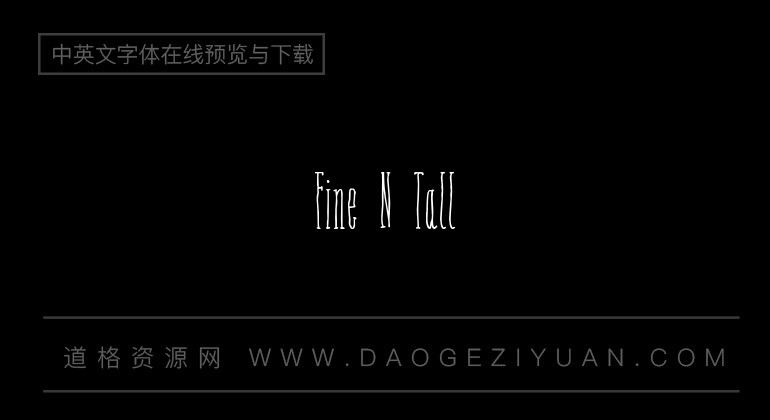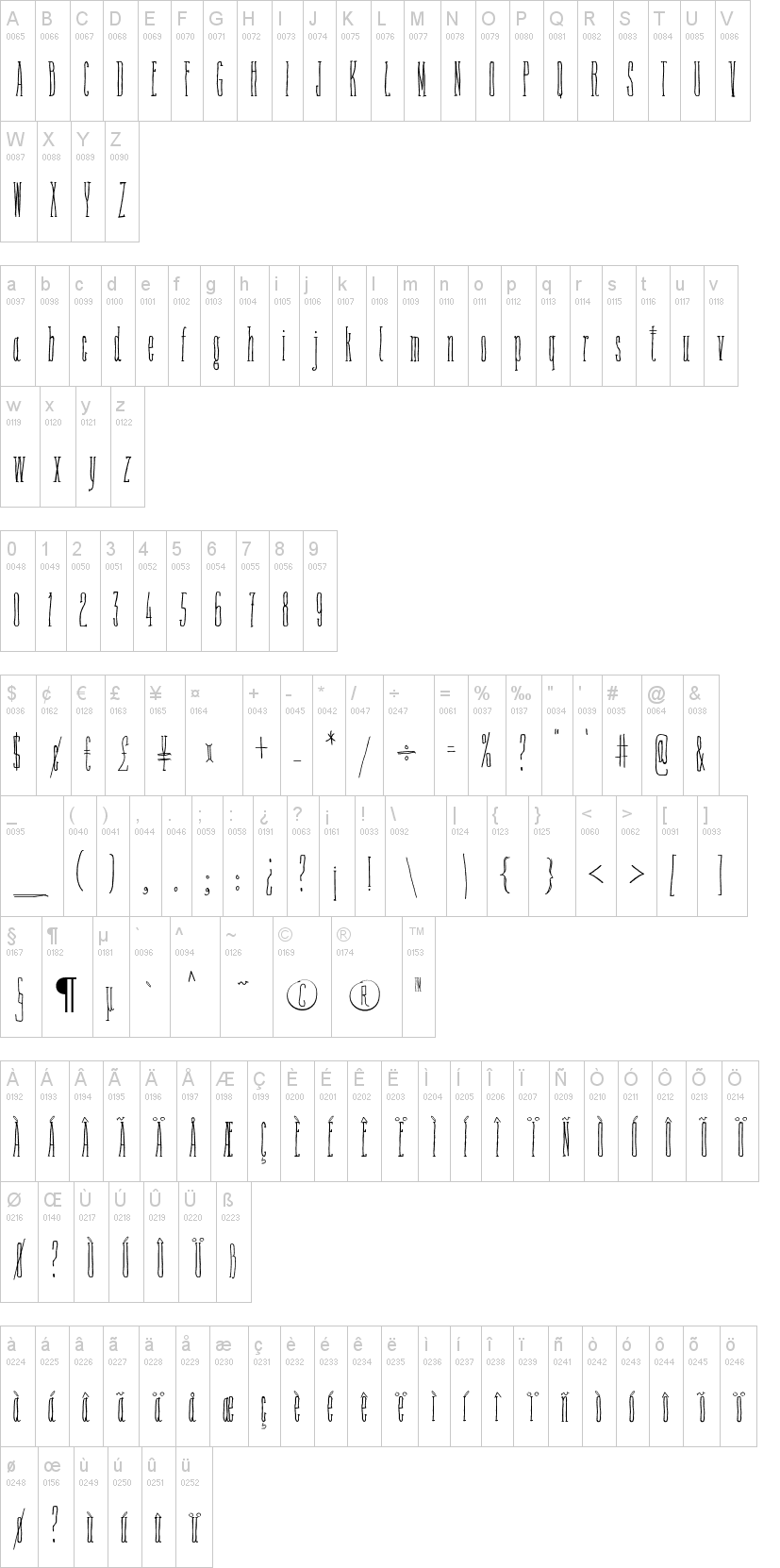
Fine N Tall
Fine N Tall 是一种非常细长的字体,由 Ray Larabie 设计。它是一种无衬线字体,具有相对较高的 x 高度,足够的字形间距和相对较窄的字符宽度。这使得 Fine N Tall 在需要窄间距或需要更多字母装入较小区域的设计项目中非常有用。Fine N Tall 字体还具有多种字重可供选择,以适应不同的设计需求。
Fine N Tall是一款非常不错的手写艺术字体,具有很好的视觉感,适合于文化类的宣传设计、商业类品牌的广告和产品包装设计以及个性化文字排版等较多场景。
Fine N Tall字符映射图